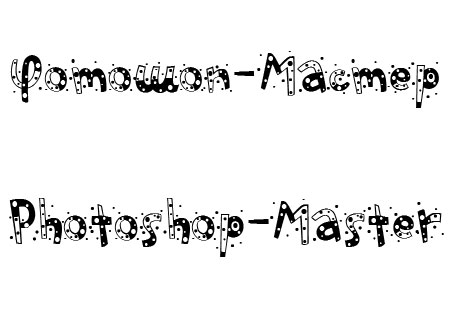
Дополнения Шрифты Татьяна Гапонова 7 августа 2009 Шрифт - PFPlayskoolPro-Confetti Необычный шрифт, с поддержкой русского языка. Скачать Шрифт - PFPlayskoolPro-Confetti
крутой! праздничный))